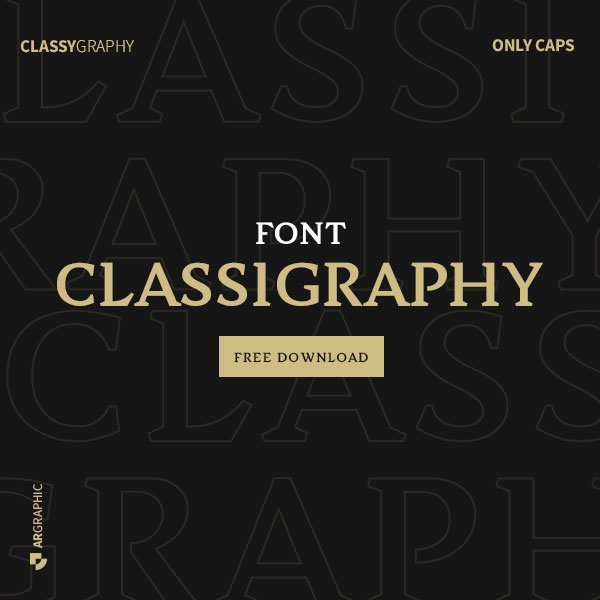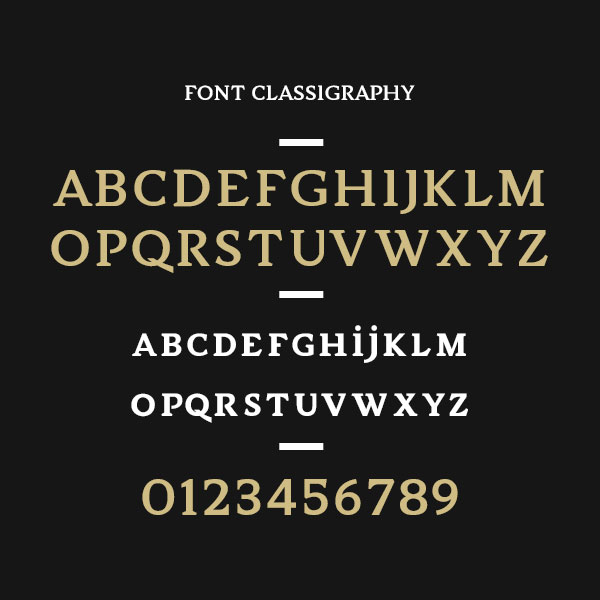
Font Classigraphy : Une police serif classique qui incarne à la fois l’harmonie et l’audace
Découvrez la beauté intemporelle de la font « Classigraphy », une police serif classique qui incarne à la fois l’harmonie et l’audace. Avec ses lignes raffinées et son caractère élégant, Classigraphy apporte une touche de sophistication à vos créations typographiques. Que vous recherchiez une typographie pour votre logo ou pour les titres de vos projets créatifs, Classigraphy se distingue par son style polyvalent qui saura captiver votre public.
Caractéristiques principales :
Style classique et harmonieux
Classigraphy incarne l’essence même de la typographie serif classique. Ses courbes élégantes et ses détails subtils rappellent le charme intemporel des anciennes œuvres typographiques, tout en apportant une touche moderne.
Touche d’audace
Ce qui distingue vraiment la font Classigraphy, c’est sa touche d’audace. Les caractères serif sont rehaussés d’une légère modernité, créant ainsi un équilibre parfait entre tradition et innovation.
Polyvalence pour les logos et les titres
Grâce à sa conception réfléchie, la font Classigraphy se prête parfaitement à la création de logos et à l’ajout de titres accrocheurs. Exprimez l’essence de votre marque ou de votre projet avec une typographie qui sait capter l’attention.
Facilité de lecture
Malgré sa touche d’audace, Classigraphy reste facilement lisible à différentes tailles de police. Chaque caractère est soigneusement dessiné pour garantir une lisibilité optimale, quel que soit le contexte d’utilisation.
Utilisation recommandée de la font Classigraphy:
Logos d’entreprise
Donnez à votre entreprise une identité distinctive en utilisant la font Classigraphy dans votre logo. L’élégance de la typographie ajoutera une dimension de crédibilité et de sophistication à votre marque.
Titres artistiques
Mettez en avant vos créations artistiques, qu’il s’agisse de graphiques, d’affiches, de brochures ou de sites web, en utilisant Classigraphy pour les titres. Créez un impact visuel fort dès le premier regard.
Projets éditoriaux
Pour les projets éditoriaux tels que les livres, les magazines ou les rapports, la typographie Classigraphy peut apporter une esthétique classique et intemporelle aux titres de chapitres et aux en-têtes.
Événements spéciaux
Faites ressortir les détails importants des invitations, des cartes de vœux et des annonces d’événements spéciaux en utilisant Classigraphy pour ajouter une touche de distinction.
Une expression de l’élégance intemporelle
Classigraphy est bien plus qu’une simple typographie serif classique. Elle est une expression de l’élégance intemporelle avec une pointe d’audace, conçue pour élever vos créations typographiques à de nouveaux sommets. Téléchargez gratuitement Classigraphy dès aujourd’hui et laissez cette typographie polyvalente embellir vos logos et sublimer vos titres avec une harmonie qui captivera vos publics. Donnez une nouvelle dimension à votre communication visuelle grâce à la splendeur unique de Classigraphy.
La font Classigraphy créée par l’agence de design graphique Argraphic
Laissez-vous inspirer par le génie créatif de l’agence de design graphique Argraphic, les esprits visionnaires derrière la conception de Classigraphy. Forts de notre engagement envers l’excellence esthétique et la perfection typographique, nous avons conçu la font Classigraphy pour incarner notre passion pour l’art du design. Avec des années d’expérience dans la création de visuels exceptionnels, l’agence Argraphic a façonné Classigraphy pour refléter la symbiose parfaite entre tradition et innovation.
Transformez vos créations en une expérience visuelle inoubliable.
Chaque lettre, chaque courbe et chaque détail ont été soigneusement élaborés pour vous offrir une typographie qui non seulement satisfait, mais aussi inspire vos besoins typographiques les plus exigeants. Découvrez la touche distinctive de l’agence Argraphic à travers la font Classigraphy et transformez vos créations en une expérience visuelle inoubliable.